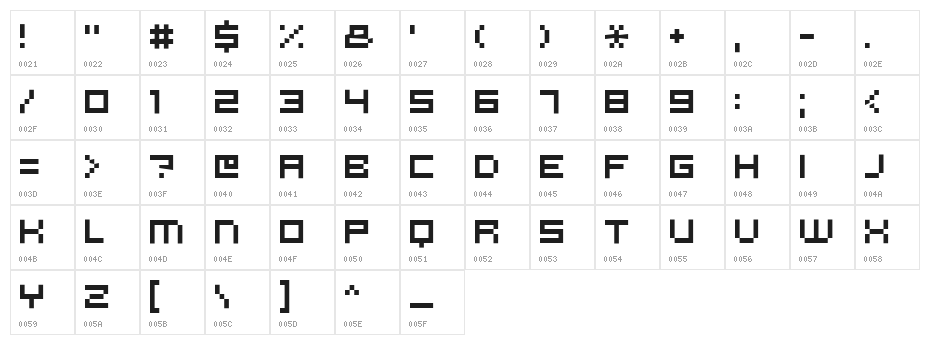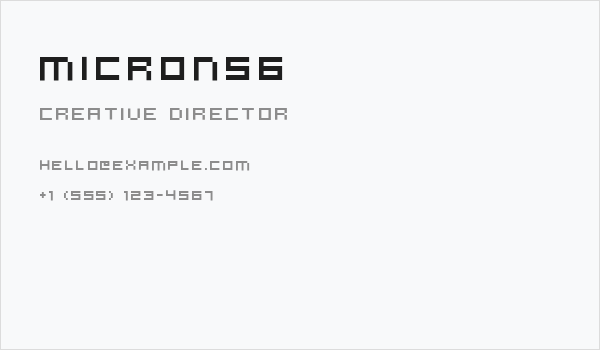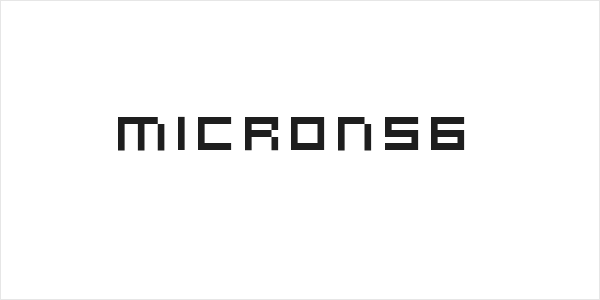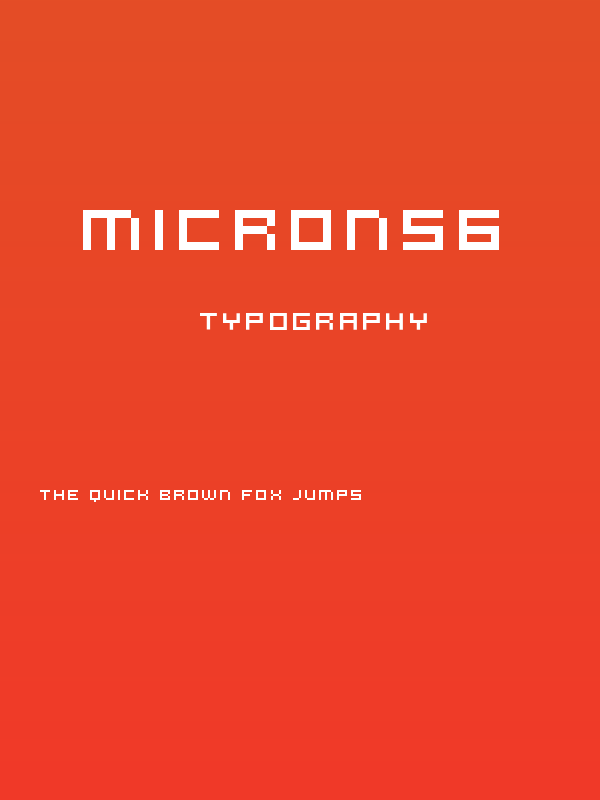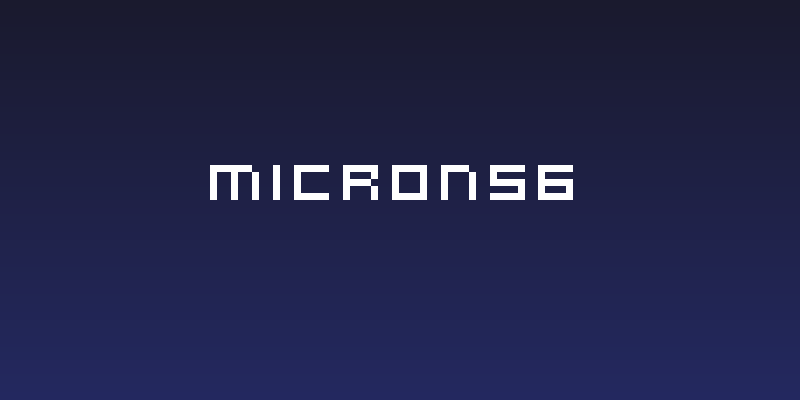
microN56 Font
| Gesamtstil | Vintage |
| Anwendungsfall | Headlines, Logos, Digital displays |
| Vorgeschlagene Projekte | Ideal for video game design, retro-themed posters, digital art projects, and any work requiring a nostalgic or tech-inspired look. |